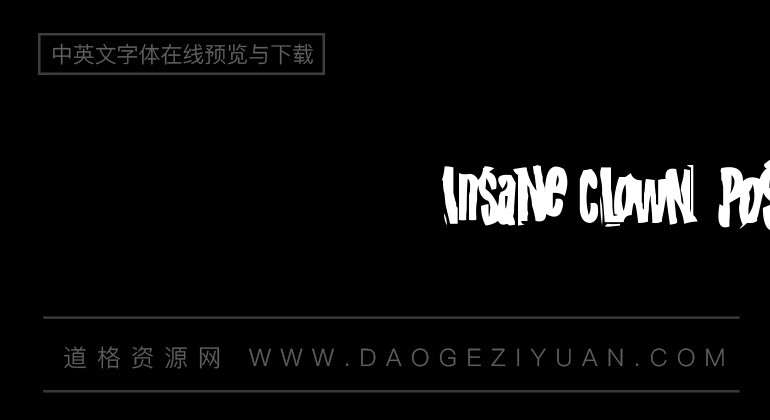
Psychopathic Font
Psychopathic Font 是一款可爱的设计字体,它有着深邃而又独特的外观,拥有超过 100 个不同的字体样式,可以用于创建多种设计效果。它可以用于创建文本、图片、视频、标题、标签等等,可以让你的设计更加独特而有趣。它还拥有丰富的字体功能,可以让你的设计更加精细,令人耳目一新。
Psychopathic Font是一款非常不错的手写艺术字体,具有很好的视觉感,适合于文化类的宣传设计、商业类品牌的广告和产品包装设计以及个性化文字排版等较多场景。